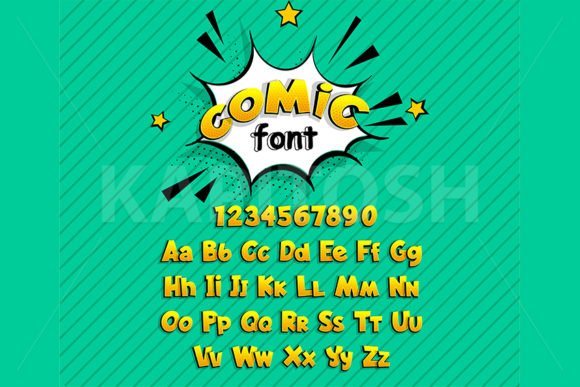
Lowercase Uppercase Yellow Comic Font
Ulasan Lengkap: Lowercase Uppercase Yellow Comic Font
Se você trabalha com design gráfico, publicidade ou produção de conteúdo visual, o Lowercase Uppercase Yellow Comic Font pode ser a peça que faltava no seu arsenal criativo. Esta fonte combina o charme retro dos quadrinhos com um toque moderno de pop‑art amarelo, proporcionando letras em lowercase e uppercase que se destacam em qualquer aplicação.
- Estilo Comic Pop Art: Design inspirado em quadrinhos clássicos, com sombras em meio‑tom que dão profundidade e dinamismo.
- Versatilidade de Uso: Ideal para interiores, anúncios, banners, pôsteres, estampas em roupas, stickers e muito mais.
- Alfabeto completo: Inclui todas as letras minúsculas e maiúsculas, números e símbolos típicos de textos de quadrinhos.
Por que escolher esta fonte?
Além da estética vibrante, a Yellow Comic Font oferece legibilidade mesmo em tamanhos pequenos, graças ao seu peso negrito e ao contraste das sombras halftone. Isso a torna perfeita para projetos que precisam chamar a atenção sem perder clareza.
Se você busca uma fonte que una energia pop‑art, legibilidade e flexibilidade de aplicação, o Lowercase Uppercase Yellow Comic Font é a escolha certa. Experimente em seu próximo banner, capa de livro ou design de camiseta e deixe seu público perceber a diferença de um estilo verdadeiramente impactante.